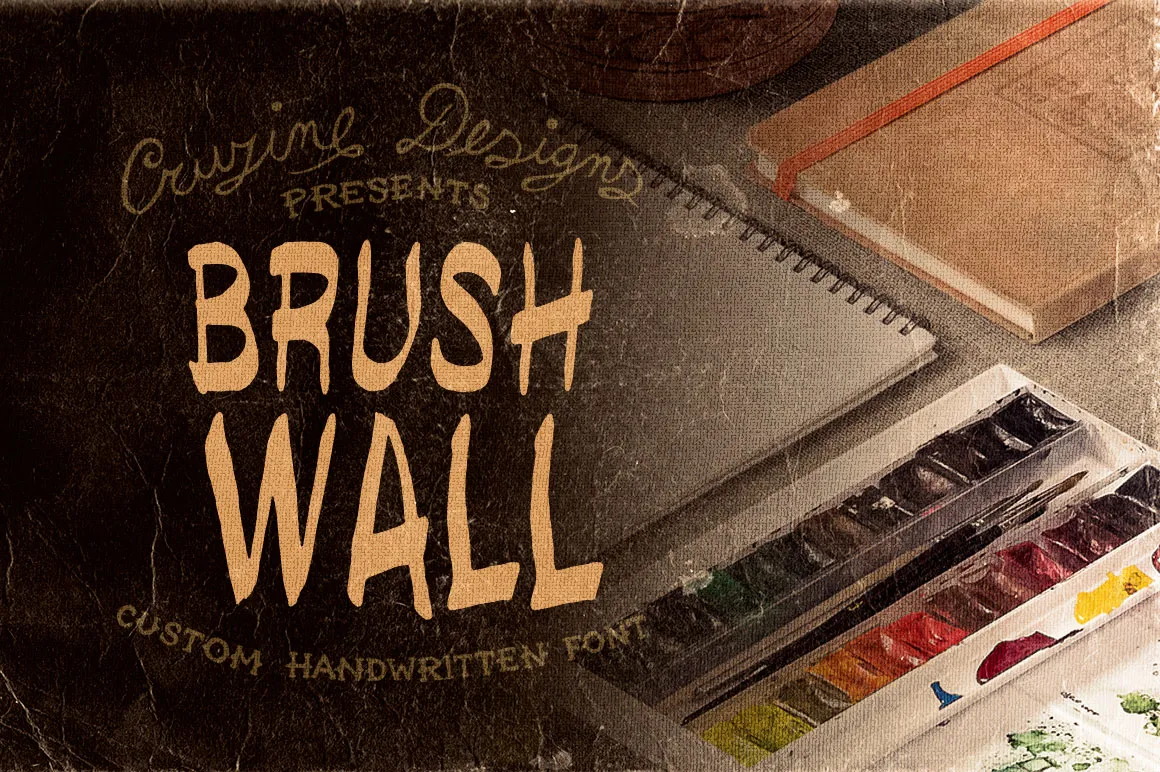
Brushwall Font
A Brushwall Font é uma elegante escolha para qualquer projeto que busque a simplicidade e a naturalidade do autogravado livre e estilo de pincel. Ela foi criada pelo talentoso designer Hamilton da Cruzine Design, trazendo um toque único à sua tipografia. Esta fonte script não apenas proporcionará um acabamento sofisticado em seus materiais digitais, mas também manterá uma conexão direta com a arte manual e o desenho livre. Seja para um design gráfico de moda ou um elemento visual de site profissional, a Brushwall oferece uma combinação perfeita de simplicidade e estilo. Descarregue-a agora e prove seu poder ao trabalhar em seus projetos!